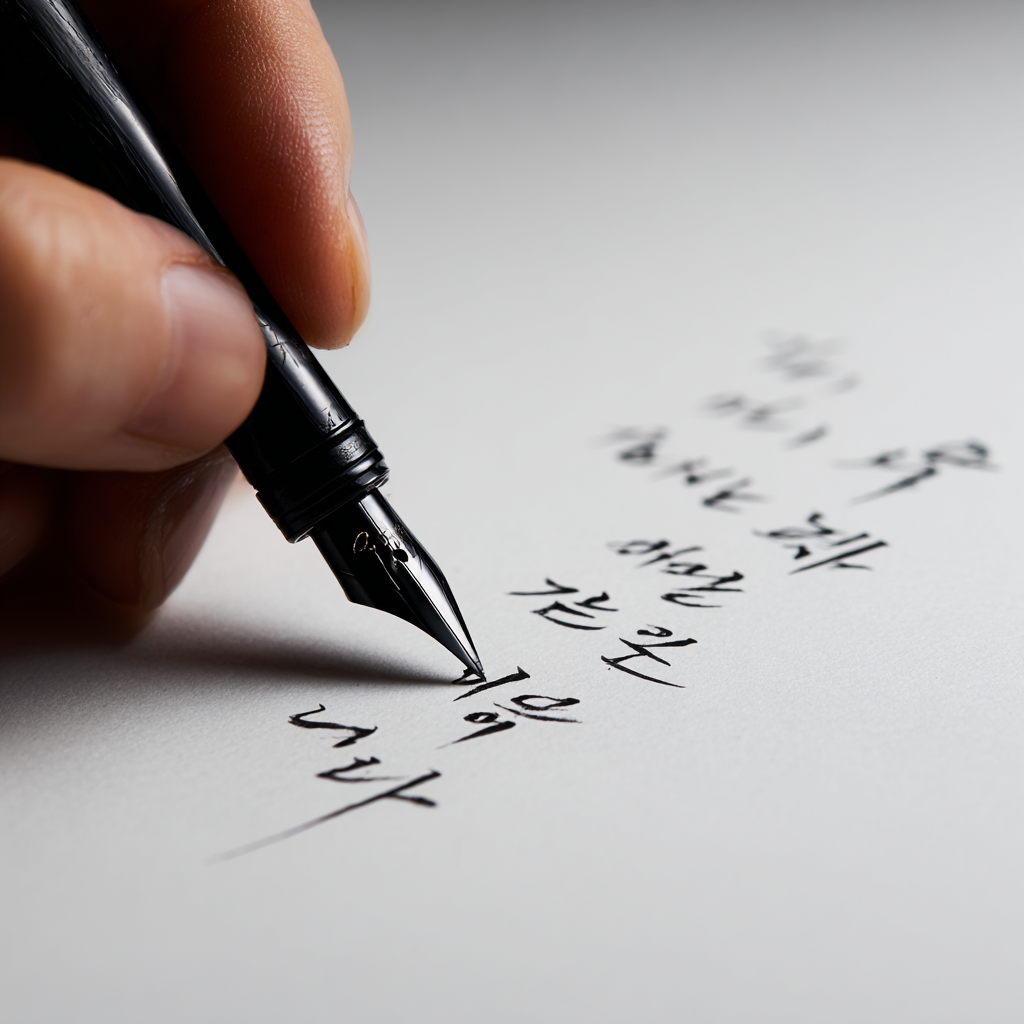
요즘 폰트 시장에서는 깔끔하고 개성 있는 손글씨 폰트가 큰 인기를 끌고 있어요. 특히 SNS나 유튜브 썸네일, 일러스트 작업, 브랜드 로고에 직접 만든 손글씨를 사용하면 따뜻하고 친근한 이미지를 줄 수 있어서 많은 창작자들이 도전하고 있답니다.
손글씨 폰트를 직접 만들어서 수익을 창출하는 사람들도 점점 늘어나고 있어요. 실제로 유명한 손글씨 폰트 하나로 수백만 원 이상 벌어들이는 사례도 많아요. 이 글에서는 손글씨 폰트를 만드는 데 필요한 도구부터 수익화까지 전 과정을 아주 꼼꼼하게 소개해볼게요 😊
✍ 손글씨 폰트의 매력과 트렌드
손글씨 폰트는 디지털 시대임에도 불구하고 아날로그 감성을 담아내는 특별한 매력을 가지고 있어요. 누군가 직접 쓴 듯한 따뜻한 느낌은 기계적으로 찍힌 활자와는 전혀 다른 감정을 전하죠. 그래서 감성 콘텐츠나 브랜딩, 유튜브 섬네일, 캘리그라피 등에 많이 활용되고 있어요.
요즘은 기업들도 브랜드에 개성을 더하기 위해 손글씨 폰트를 활용하는 사례가 늘고 있어요. '배민체', '빙그레체', '교보손글씨체'처럼 브랜드 아이덴티티를 살린 전용 폰트들이 좋은 예죠. 이처럼 폰트 자체가 브랜드 자산이 되는 시대예요.
특히 MZ세대를 중심으로 DIY 문화와 창작 열풍이 확산되면서, 자신만의 폰트를 만들어보고 싶어하는 사람들도 많아졌어요. 나만의 글씨체가 폰트로 만들어지고, 또 누군가가 그것을 사용한다는 건 굉장히 뿌듯한 경험이에요.
실제로 SNS를 통해 폰트를 공개하고 반응을 얻거나, 폰트 마켓에 등록해 수익을 얻는 개인 창작자들이 해마다 증가하고 있어요. "내 글씨로 돈 벌 수 있어요?"라고 묻는다면, 지금은 정말 그럴 수 있는 시대라고 말할 수 있어요 😎
📊 손글씨 폰트 활용 분야별 예시
활용 분야 예시 포인트 SNS 콘텐츠 인스타그램, 유튜브 썸네일 감성적 & 눈에 띄는 글씨 브랜드 로고 디저트샵, 카페 BI 개성 있는 첫인상 출판 디자인 동화책, 에세이 표지 부드러운 분위기 굿즈 제작 스티커, 엽서, 포스터 직접 만든 감성 전달 내가 생각했을 때 손글씨 폰트의 가장 큰 매력은 ‘따뜻함’이에요. 컴퓨터로 정갈하게 정리된 폰트도 좋지만, 내 손으로 직접 쓴 듯한 폰트가 주는 정서는 디지털 시대에도 여전히 사람들의 마음을 사로잡고 있어요.
🛠 손글씨 폰트 제작 도구 소개
손글씨 폰트를 만들기 위해 필요한 도구는 생각보다 간단해요. 기본적으로는 종이와 펜만 있어도 시작할 수 있고, 요즘은 디지털로 바로 제작할 수 있는 프로그램들도 많아서 훨씬 쉬워졌답니다. 간단한 드로잉 앱과 폰트 변환 툴만 있으면 나만의 폰트를 손쉽게 만들 수 있어요!
처음에는 아이패드나 갤럭시탭 같은 태블릿과 ‘프로크리에이트(Procreate)’, ‘어도비 프레스코(Adobe Fresco)’ 같은 드로잉 앱을 활용해 손글씨를 쓸 수 있어요. 종이에 쓴 후 스캔해서 사용하는 방법도 있지만, 요즘은 디지털 방식이 훨씬 간편하답니다.
그 다음 단계는 손글씨를 폰트 파일로 변환해주는 툴이에요. 대표적으로는 ‘Calligraphr’, ‘FontForge’, ‘Glyphs’, ‘Fontself’ 같은 프로그램들이 있어요. 그중 Calligraphr는 웹 기반이고 무료로도 시작할 수 있어서 처음 입문자에게 특히 추천돼요 ✨
좀 더 고급 기능을 원한다면 Glyphs(맥 전용), FontLab 같은 전문 프로그램을 사용하는 것도 좋아요. 이들 프로그램은 커닝, 힌팅, 베지어 곡선 편집 등 세밀한 작업이 가능해요. 초보자라면 Calligraphr → FontForge 조합부터 천천히 시작해보는 게 좋아요 😊
🔧 손글씨 폰트 제작 도구 비교표
도구 플랫폼 특징 추천 대상 Calligraphr 웹 간편한 폰트 생성 입문자 FontForge 윈도우/맥 오픈소스, 고급 편집 중급자 Glyphs 맥 전용 정밀한 폰트 제작 전문가 Fontself Adobe 확장 일러스트레이터 연동 디자이너 처음엔 도구 이름만 들어도 복잡해 보일 수 있지만, 막상 해보면 생각보다 간단하다고 느껴질 거예요. 폰트 제작은 ‘내 글씨를 누군가 쓰는’ 멋진 경험으로 이어질 수 있어서 도전해볼 만한 가치가 충분하답니다 💡
📝 폰트 제작 과정 한눈에 보기
손글씨 폰트를 만드는 전체 과정은 생각보다 단순한 단계로 구성돼 있어요. 크게 나누면 ① 손글씨 작성 → ② 스캔 또는 디지털 드로잉 → ③ 폰트 변환 툴에 불러오기 → ④ 글자 정렬 및 커닝 설정 → ⑤ 내보내기(.ttf/.otf)로 진행돼요. 과정만 알면 누구나 도전 가능하죠 💪
첫 번째 단계는 알파벳, 한글 자음·모음, 숫자, 특수기호 등을 A4 용지 혹은 태블릿에 정리해 손글씨로 써 내려가는 거예요. 종이에 쓸 경우엔 나중에 스캔해서 업로드하면 되고, 디지털로 작성했다면 바로 이미지로 저장할 수 있어요.
그다음은 이미지 파일을 폰트 생성 도구(Calligraphr 등)에 불러오는 단계예요. 글자마다 경계를 설정하고, 각 글자가 어떤 유니코드에 해당하는지 입력해줘야 해요. 여기서 자동 인식 기능이 있어 시간을 많이 절약할 수 있답니다.
마지막으로 ‘커닝(Kerning)’ 작업을 통해 글자 간격을 손봐주고, '베이스라인'과 높낮이를 조정해주면 폰트가 보다 자연스러워져요. 그렇게 다듬어진 폰트를 TTF나 OTF 형식으로 저장하면, 윈도우나 맥에서도 설치해 쓸 수 있어요 🙌
🪄 손글씨 폰트 제작 단계 요약
단계 설명 팁 1. 손글씨 작성 자음/모음/숫자 등을 직접 작성 일정한 크기와 간격 유지 2. 이미지 저장 스캔 또는 PNG로 저장 흰 배경, 선명한 이미지 사용 3. 폰트 툴에 업로드 글자 매핑 및 이름 설정 자동 정렬 기능 활용 4. 커닝 및 수정 글자 간격 조정 자연스럽게 이어지는 느낌으로 5. 폰트 파일 출력 TTF/OTF 파일로 저장 윈도우, 맥 호환 체크 이 과정을 한두 번 반복해보면 금방 익숙해질 수 있어요. 처음엔 불편하게 느껴질 수도 있지만, 내가 만든 글씨가 진짜 폰트가 되어 다양한 사람들에게 쓰인다는 건 정말 뿌듯한 일이에요 😊
🎨 개성 있는 폰트 디자인 팁
폰트는 단순히 글자를 표현하는 도구를 넘어서, 감성과 메시지를 담는 그릇이에요. 손글씨 폰트를 만들 때 가장 중요한 건 바로 ‘개성’이에요. 내 글씨만의 특징이 드러나야 다른 사람도 그 폰트를 보고 ‘아, 이건 특별하다!’ 하고 느낄 수 있답니다 🧡
먼저 획의 굵기와 속도를 일정하게 유지하는 연습을 해보는 게 좋아요. 너무 삐뚤거나 가늘고 굵은 차이가 심하면, 인쇄나 디지털에서 보기 불편할 수 있어요. 하지만 너무 똑같이 맞추려고 애쓰기보다는, 자연스러운 흐름을 유지하는 게 더 중요해요.
자신의 감성을 표현할 수 있는 테마를 먼저 정해보는 것도 좋은 전략이에요. 예를 들어 ‘빈티지한 일기장 느낌’, ‘귀여운 초등학생 글씨체’, ‘세련된 붓글씨 스타일’처럼요. 이렇게 테마가 있으면 글자의 형태나 디테일에도 일관성이 생겨요 🎯
또한 자음과 모음의 비율, 받침의 위치, 글자의 균형 등도 디자인적으로 신경 써야 해요. 너무 위로 몰리거나 아래로 쳐지면 보기 불편하거든요. 특히 한글은 받침 구조가 많아서, 중성(모음)과 종성(받침)의 조화를 고려해야 자연스러워요.
🎨 손글씨 폰트 스타일 요소 정리
요소 설명 디자인 팁 획의 굵기 글자의 선 굵기 일정하게 유지하되 개성 살리기 기울기 글자의 경사도 기울기를 전체적으로 통일 자간/행간 글자/줄 간격 너무 좁거나 넓지 않게 적당히 개성 요소 하트, 점, 물결 등 과하지 않게 포인트만 사용 정렬 기준선과 맞는 균형 중심축이 흐트러지지 않게 폰트를 디자인할 때는 나만의 정체성을 드러내는 것이 핵심이에요. 누군가는 부드러운 곡선을 살리고, 누군가는 일부러 삐뚤삐뚤한 느낌을 강조하기도 해요. 결국 폰트는 ‘감정’을 전달하는 수단이니까요 💫
📦 배포 및 마케팅 전략
완성된 손글씨 폰트를 많은 사람들에게 알리기 위해서는 배포 채널과 마케팅 전략이 중요해요. 아무리 예쁜 폰트를 만들어도, 사람들에게 노출되지 않으면 사용되지 않거든요. 그래서 처음엔 적절한 플랫폼에 올리고, 다양한 방식으로 홍보하는 게 필요해요 📢
가장 많이 활용되는 배포 플랫폼으로는 눈누(https://noonnu.cc), 다폰트(https://dafont.com), 폰트쉐어(Fontshare), Behance 등이 있어요. 국내외 사용자에게 노출되기 위해 눈누와 다폰트를 병행하는 게 좋아요. 특히 눈누는 무료 폰트 등록 시 빠르게 퍼질 수 있어요.
해외 사용자를 타겟팅하고 싶다면 Google Fonts 또는 Creative Market, MyFonts 같은 상업 플랫폼에 등록하는 방법도 있어요. 이 플랫폼들은 어느 정도 품질 기준이 있기 때문에 제출 전 검수와 포트폴리오 정리가 필요해요.
SNS 홍보도 매우 효과적이에요. 인스타그램, 유튜브 쇼츠, 블로그에 폰트를 적용한 예시 이미지나 짧은 제작 과정을 올리면 사용자들의 관심을 끌 수 있어요. 특히 영상으로 “이런 느낌의 글씨체예요~” 하고 보여주면 다운로드로 이어질 확률이 높아요 🎥
🌐 폰트 배포 채널 비교표
플랫폼 타겟 특징 수익화 눈누 국내 사용자 무료 배포에 강함 홍보 중심 다폰트 전 세계 트래픽 높음 기부 링크 가능 Creative Market 디자이너 유료 판매 수익 창출 Behance 포트폴리오 디자이너 간 공유 직접 수익은 없음 요약하자면, 처음에는 ‘무료 배포 + SNS 홍보’로 입지를 다지고, 이후 상업 플랫폼으로 확장하는 전략이 가장 좋아요. 내 폰트가 다양한 곳에서 쓰일 수 있도록 배포 채널을 잘 조합해보세요 💼
💰 폰트 수익화 방법
손글씨 폰트를 통해 수익을 얻는 방법은 생각보다 다양해요. 단순히 '판매'만이 아니라, 라이선스를 기반으로 한 계약, 제휴, 후원 등의 방식도 있답니다. 폰트는 한 번 만들어두면 꾸준한 패시브 인컴이 될 수 있어서 창작자들 사이에서 점점 인기 있는 수익 모델이 되고 있어요 💸
가장 기본적인 방법은 직접 판매예요. Creative Market, MyFonts, Gumroad, Tictail 등 디지털 콘텐츠 마켓에 등록하면 국내외 사용자에게 유료로 판매할 수 있어요. 특히 MyFonts는 전 세계 디자이너들이 애용하는 만큼 노출 효과도 크고 수익 비율도 괜찮아요.
Q5. 한글과 영어 모두 만들 수 있나요?
A5. 당연하죠! 유니코드 범위 내에서 한글, 영문, 숫자, 특수문자까지 모두 넣을 수 있어요. 다만 시간은 조금 더 걸릴 수 있어요.
Q6. 폰트 이름은 어떻게 정하나요?
A6. 본인의 닉네임, 성격, 감성을 담아 정하면 좋아요. 예: ‘민지의봄글씨’, ‘아침햇살체’, ‘몽글몽글손글씨’ 같은 이름이 인기 있어요.